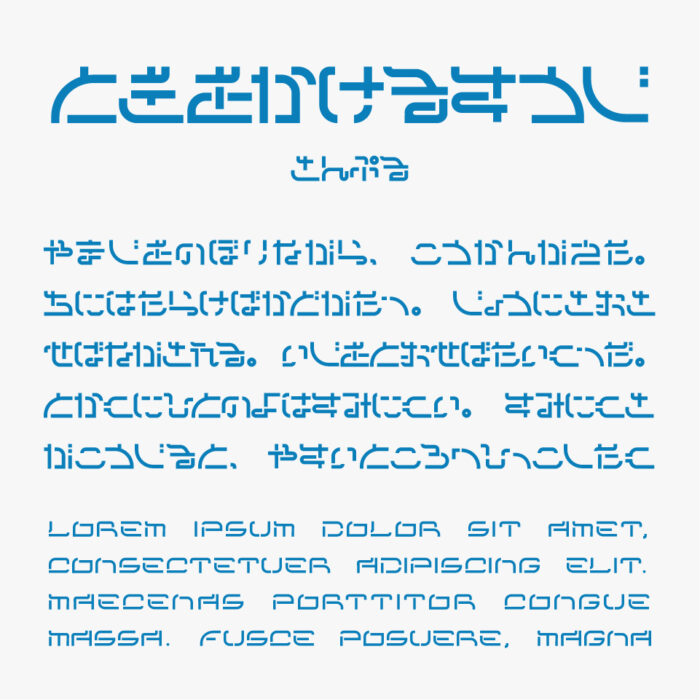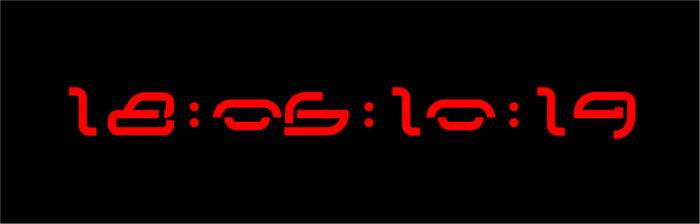
時をかける数字
時をかける数字フォントは、アニメ「時をかける少女」に登場する数字がモチーフのデザインフォントです。
デジタル時計のように、文字にスリットがデザインされているユニークなフォントです。
細く繊細なラインは無機質な構成になっていることで、SFや近未来ちっくな雰囲気を感じるかっこいいデザインフォントです。
劇中のような時間を打ち込むとこのような感じになります。再現度が高い!